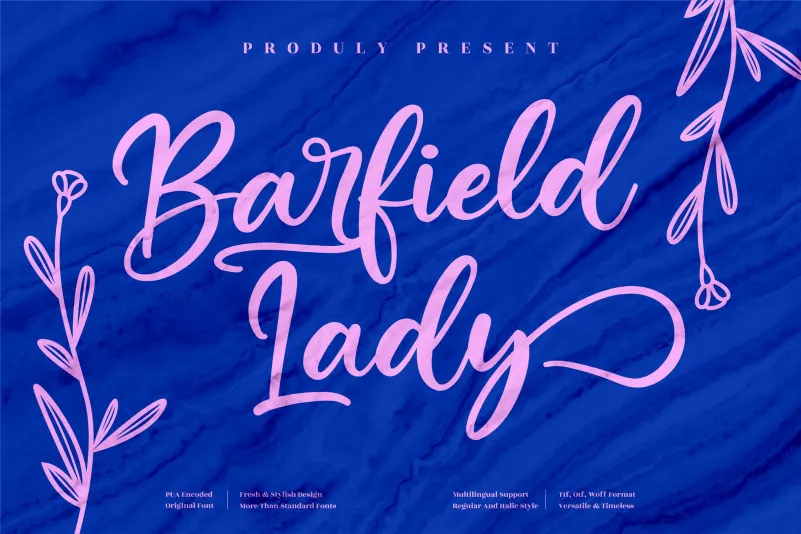
A fonte ‘Barfield Lady Font’ é uma elegante tipografia romântica perfeita para qualquer projeto onde há necessidade de adicionar um toque delicado e sofisticado à sua criação. Sujeitável a logos, projetos de marca, designs de móveis de casa, embalagens de produtos, tigelas, mensagens, postais, sacolas de shopping, camisetas, capas de livros, cartões de visita, cartas de aniversário, etiquetas, fotografia e até mesmo marcas em eventos especiais. Suavemente delicada e com um toque artesanal, esta fonte enriquece seus projetos e o torna único. Seja para adicionar um charme aos mais variados tipos de trabalhos gráficos, ‘Barfield Lady Font’ é a escolha perfeita.